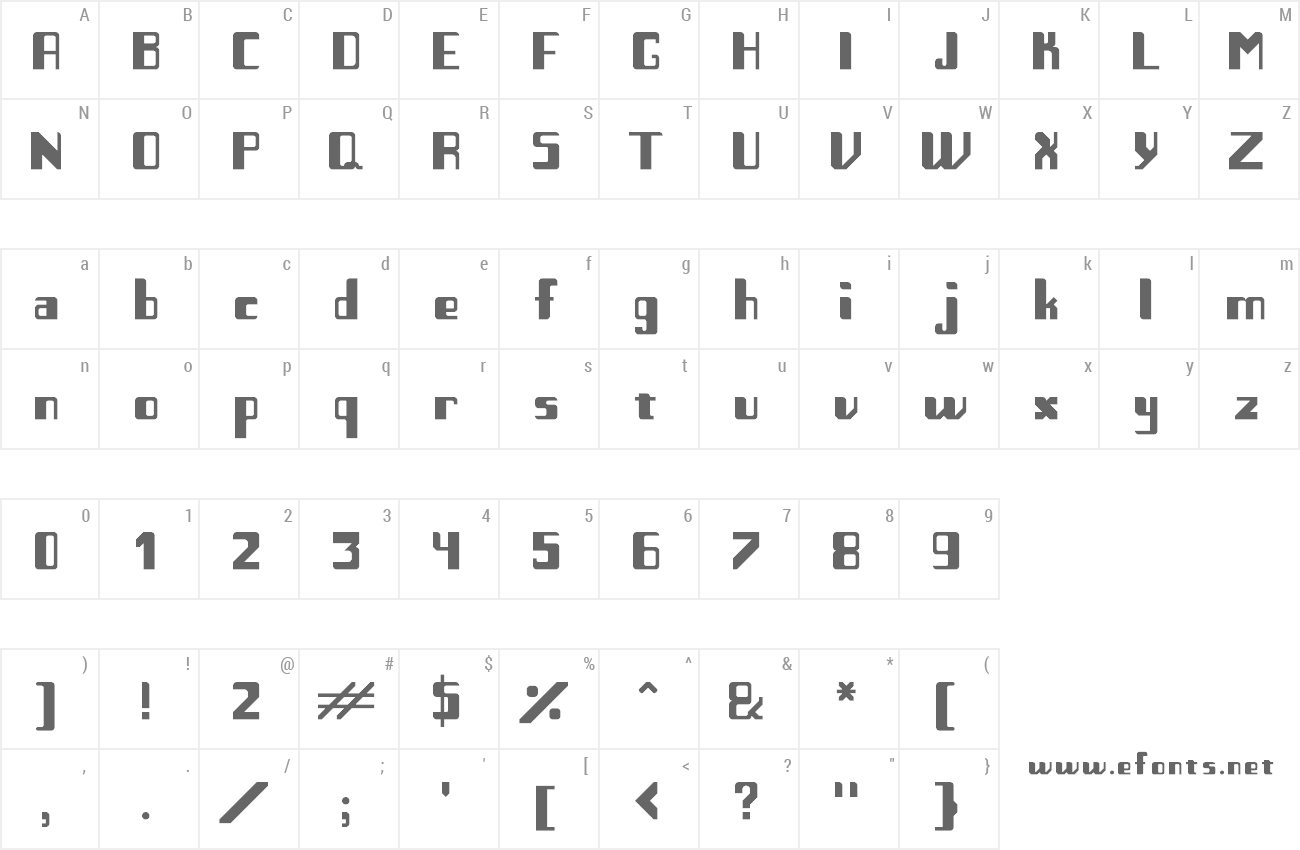
| Font name: | Tipografia |
| Author: | Rebeca da Silva |
| Note by Rebeca da Silva | |
| Fonte criada na faculdade de Tecnologia Senac Rio na disciplina de Tipografia Digital, curso de Design Gráfico. |